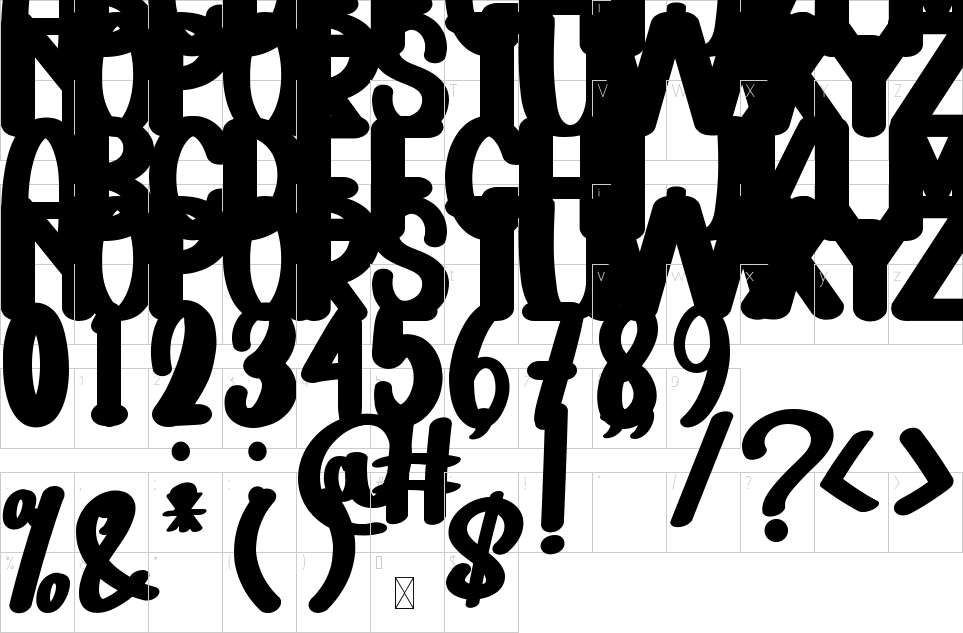
A Ashton Font é uma opção perfeita para designers gráficos, amantes de fontes gratuitas e qualquer um que busque uma paleta de estilo elegante e sofisticada. Desenvolvida pelo InermediaSTUDIO, essa fonte foi projetada para proporcionar uma experiência visual agradável em ambos Windows e Mac. Com seu design cuidadosamente pensado, a Ashton Font oferece uma versatilidade que se adapta a vários tipos de projetos, desde editoriais até design gráfico em 3D. Seu baixo número de downloads (659) sugere que muitos usuários estão se beneficiando de sua estética refinada e funcionalidade robusta. Ideal para aqueles buscando um toque diferenciado em seus trabalhos, a Ashton Font é um download que você não encontrará em outros lugares, garantindo uma combinação única de estética e funcionalidade.